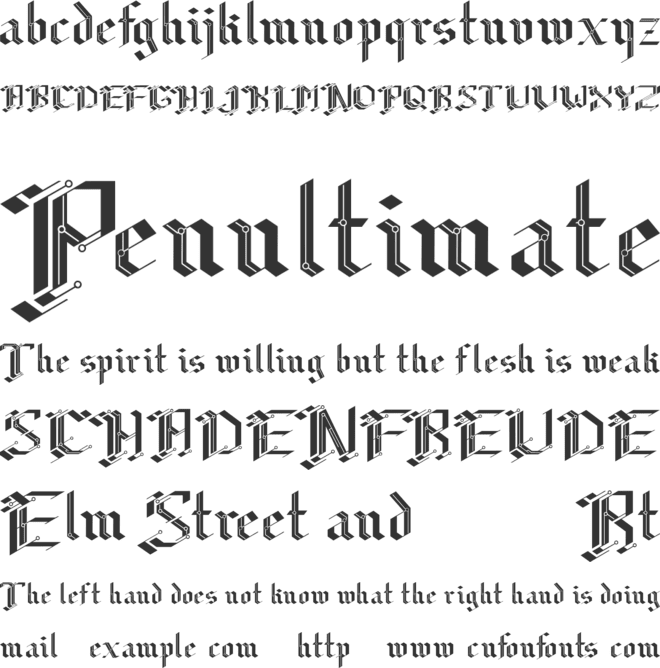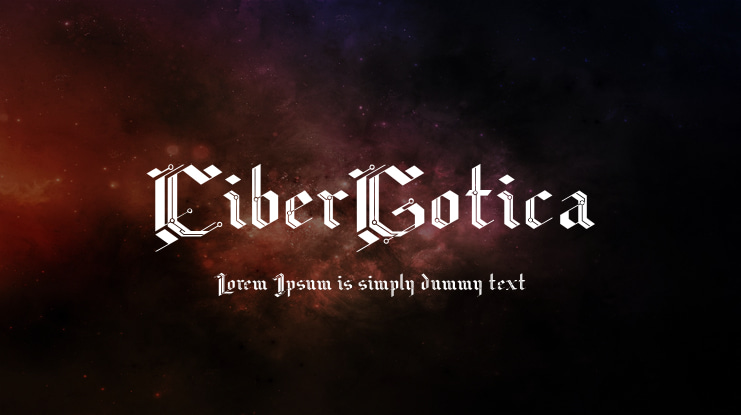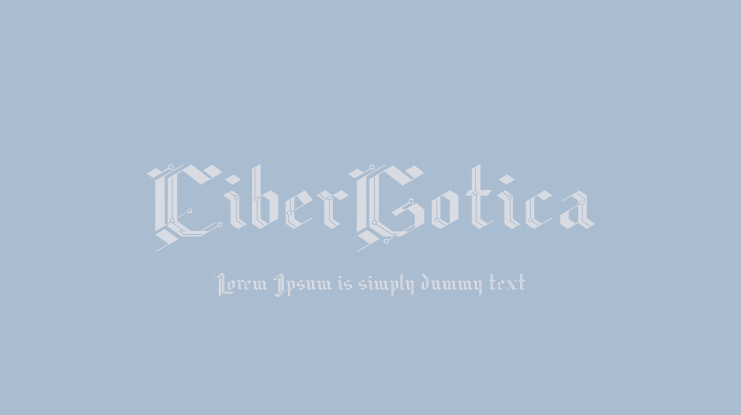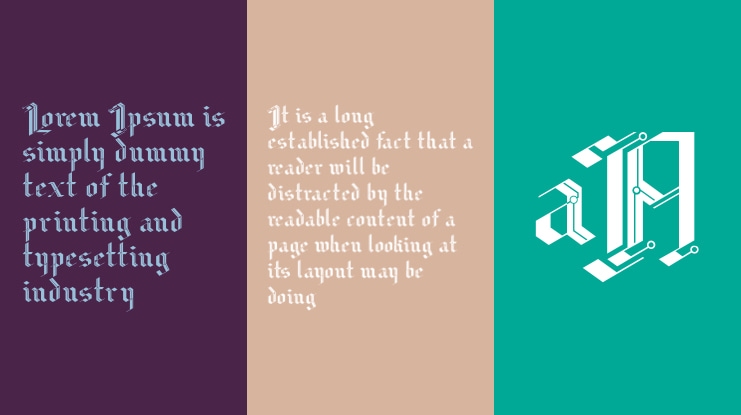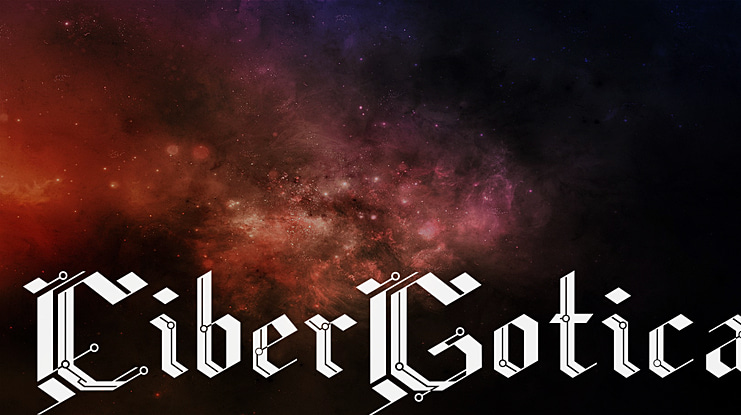
CiberGotica Font
A CiberGótica realiza uma releitura da gótica escrita, contrastando o contexto conceitual-histórico do tipo gótico com a era maquínica-digital contemporânea, ilustrada pelas placas de circuitos impressos a parte mais sólida de um dos alicerces do mundo líquido.